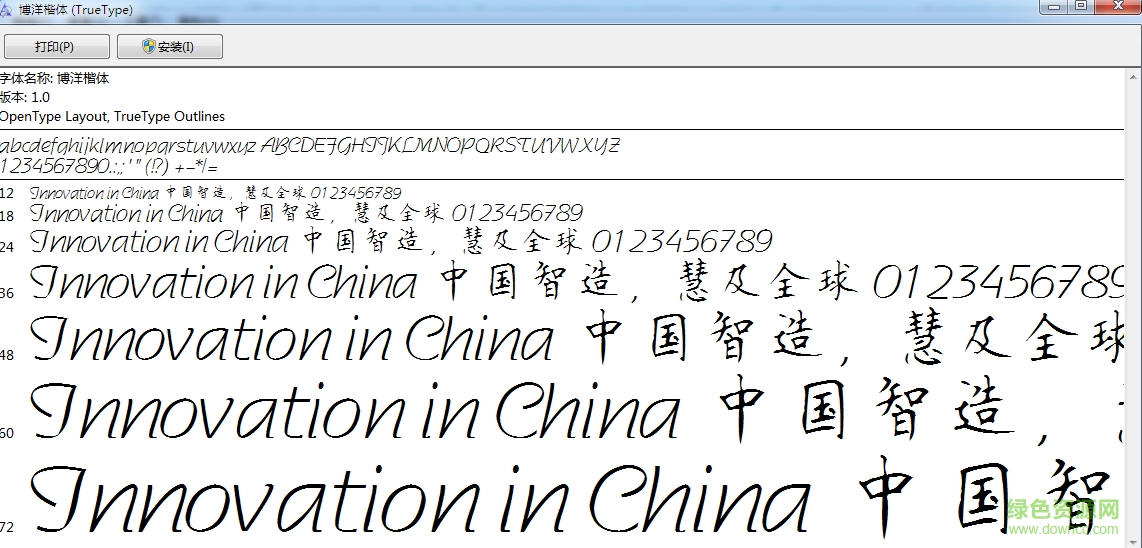
博洋楷體字體是一款楷書體電腦字體,這款字體字與字排列在一起時大小勻稱、行款整齊,筆畫和部首均衡分布、重心平穩(wěn)、比例適當、字形端正,非常適合用于藝術(shù)創(chuàng)作,喜歡可以來綠色資源網(wǎng)下載試用!
博洋楷體是一款完美繼承楷體筆劃平正,結(jié)體整齊,工妙于點畫,神韻于結(jié)體。平正而不呆,齊整而不拘特點的電腦字體,字體看上去起收有序、筆筆分明、堅實有力,又停而不斷、直而不僵、彎而不弱、流暢自然.